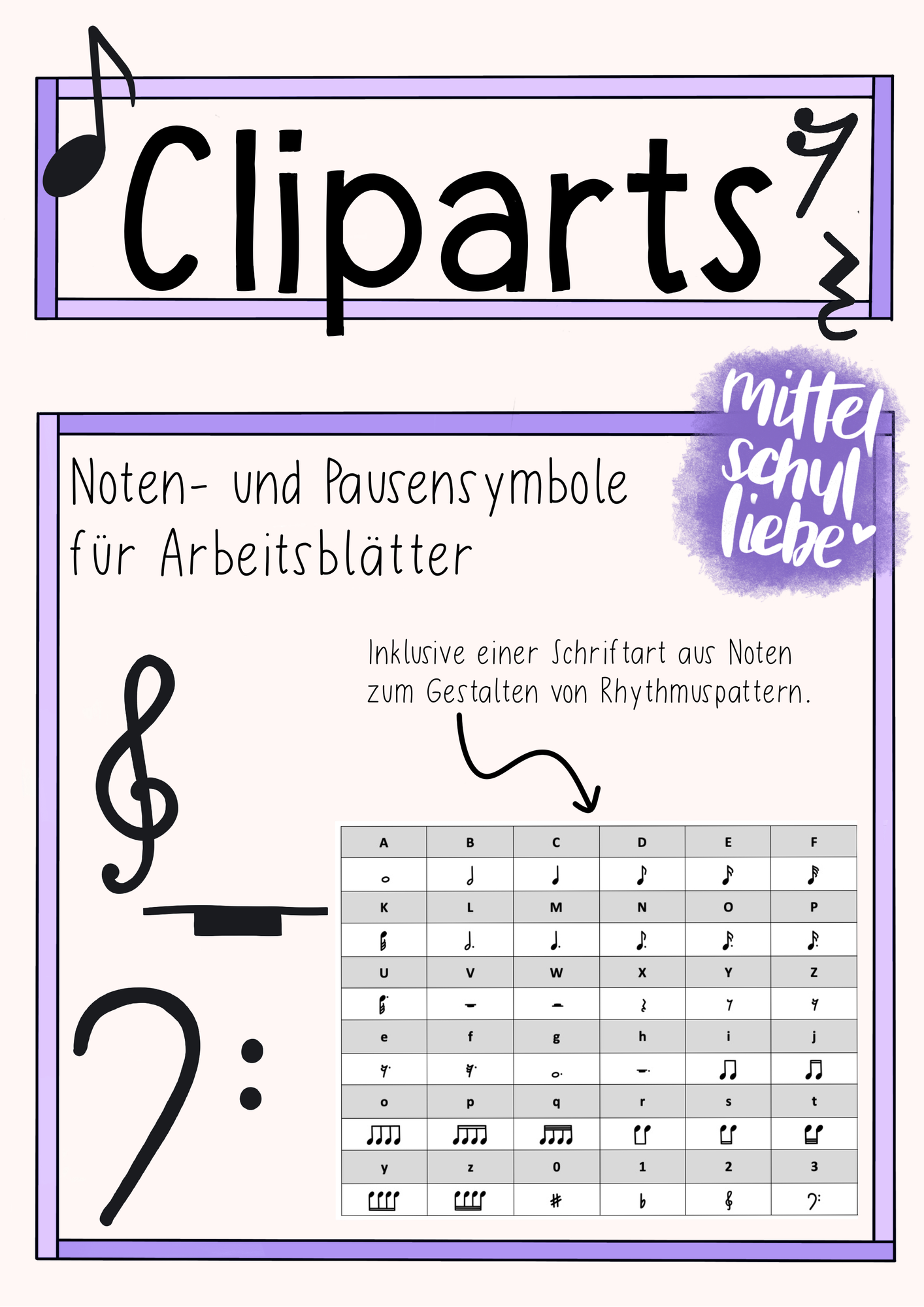
Dieses Material enthält eine Notenschrift und 20 Notencliparts zum Gestalten von Unterrichtsmaterialien für den Musikunterricht.
Mit der Notenschrift lassen sich ganz leicht in Word o. ä. Rhythmuspattern erstellen.
Schriftart "Notenliebe" und 20 Cliparts für den Musikunterricht